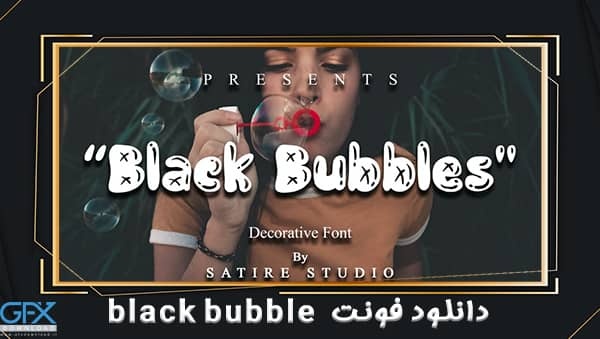
فونت رایگان زیبای Black Bubbles
دانلود رایگان فونت زیبای تزیینی Black Bubbles
این فونت زینتی بسیار زیبا برای دعوتها مانند کارت های تبریک ، مواد مارک تجاری ، کارت های کسب و کار ، نقل قول ها ، پوسترها و موارد دیگر مناسب است! فونت رایگان زیبای Black Bubbles با فرمت های OTF & TTF مناسب برای رایانه و مک می باشد. کاملاً بدون نرم افزار طراحی اضافی قابل دسترسی است. نصب های ساده -قابل دسترسی در Adobe Illustrator ، Adobe Photoshop ، Adobe InDesign ، حتی روی Microsoft Word کار کنید.